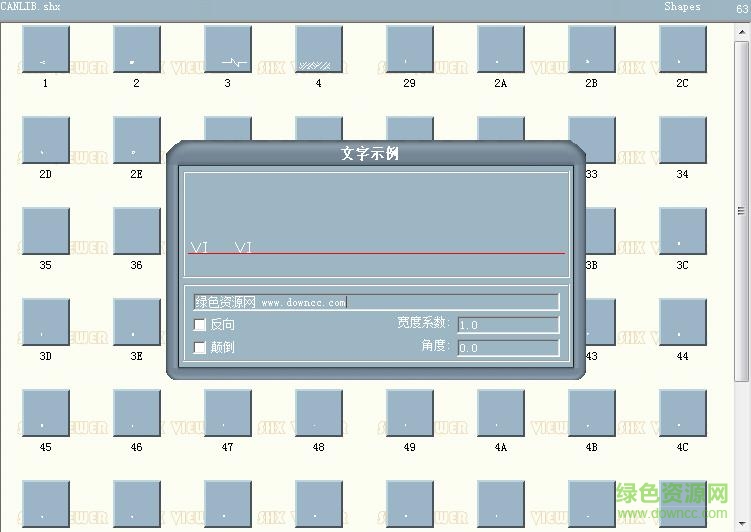
canlib.shx在日常制圖中能夠帶來符號輸入的效果,擁有十分快速的字體符號調(diào)用功能,同時滿足眾多行業(yè)的字符需求,通過這款cad字體能夠制作出眾多復合要求的圖紙!
大字體是用SHX(形文件)生成的(筆畫是單線條)單線形雙字節(jié)字體.
與左面SHX字體的區(qū)別是:
左面SHX字體是用于如英文、拉丁字母的字體或符號(如形位公差符號),文件大小僅有幾十K以內(nèi)。
它用于如中文等復雜的雙字節(jié)文字,字體文件大小在數(shù)百K以上。